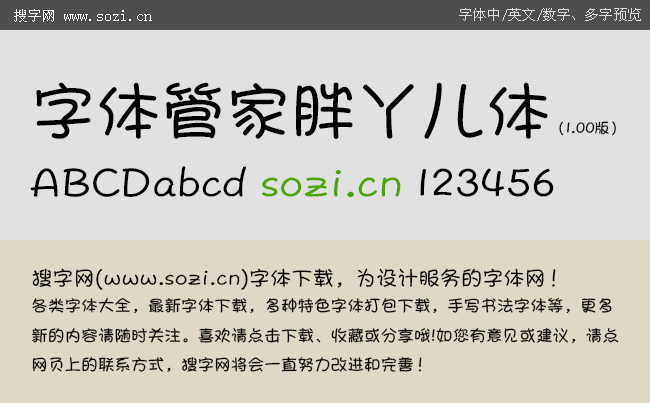
字體管家胖丫兒體
搜字網(wǎng)提供一款字體管家胖丫兒體中文藝術(shù)字體下載,字體管家胖丫兒體是一款非常實(shí)用的字體,以獨(dú)特的彎曲風(fēng)格和俏皮的樣式給你很好的視覺效果,可用于印刷出版、包裝設(shè)計(jì)、廣告設(shè)計(jì)、網(wǎng)頁設(shè)計(jì)等。